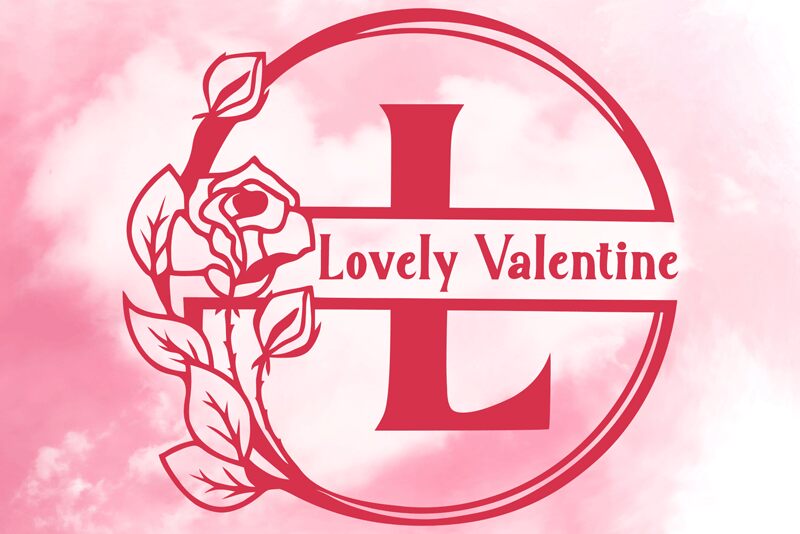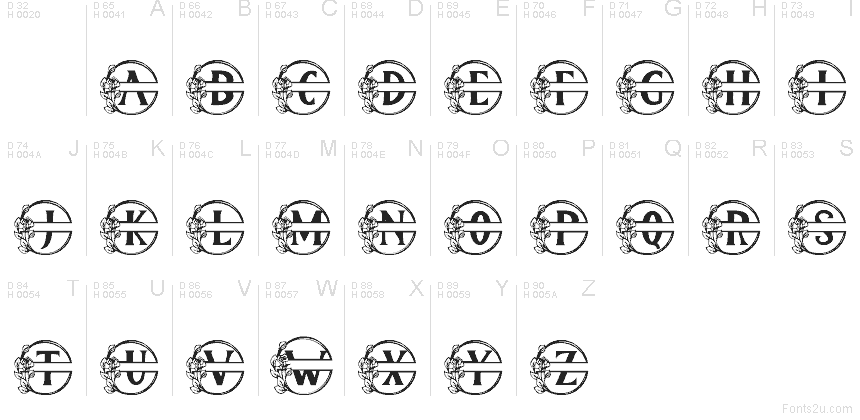
Monogram Lovely
Monogram Lovely de Yoga Letter es una tipografía decorativa display gratuita con un estilo de monograma, que muestra una inicial serif grande enmarcada por un borde circular y un arreglo floral en uno de sus lados. La forma de la letra es centrada y formal, mientras que las rosas y hojas suavizan la estructura con un toque ornamental y hecho a mano.
Monogram Lovely funciona de maravilla para invitaciones de boda, tarjetas de identificación, logotipos, etiquetas de regalo y empaques boutique, ya que la corona incorporada ofrece un diseño central impecable sin necesidad de mayor decoración. Esta tipografía gratuita también se adapta a iniciales personalizadas, sellos de monograma, detalles en papelería y gráficos para redes sociales cuando necesitas que una sola letra luzca elegante y personal.